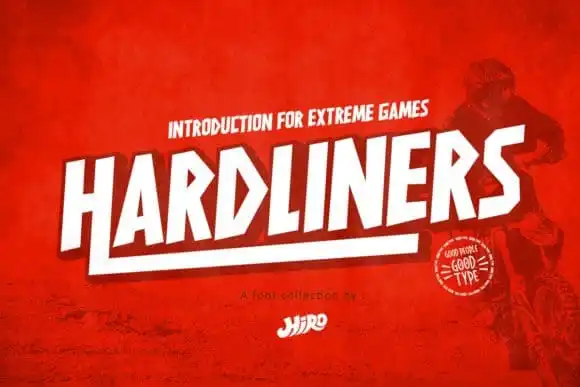
Hardliners Display Font – Download Grátis
A Hardliners Display Font é uma nova tipografia exibição agressiva que abraça o estilo retrô com elegância contemporânea. Seu design fornece formas abstractas que revelam a beleza vibrante e diversificada de uma linguagem visual tão versátil quanto inteligente. Esta fonte se destacará em uma variedade ampla de contextos, tornando-a ideal para ambientes onde um forte impacto visual é essencial. Seja para logotipos agressivos ou escrita imponente, a Hardliners Display Font se transforma na escolha perfeita para qualquer projeto que valorize o poder do design gráfico.